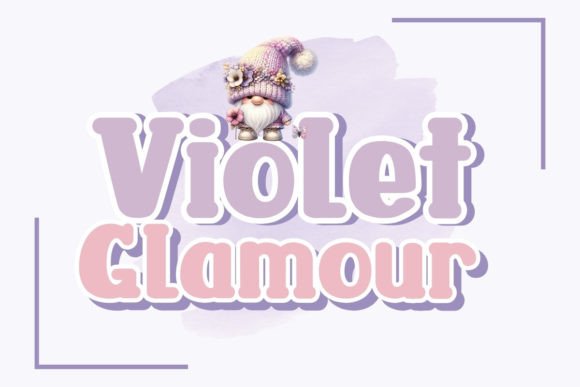
Violet Glamour
Nếu bạn đang tìm kiếm các tài nguyên chất lượng cao như Violet Glamour, gói cao cấp này là một lựa chọn tuyệt vời cho các dự án sáng tạo của bạn.
Cho dù bạn đang tạo sản phẩm POD (In theo yêu cầu), thiệp mời đám cưới hay đồ họa mạng xã hội, Violet Glamour đều là một sự lựa chọn lý tưởng.